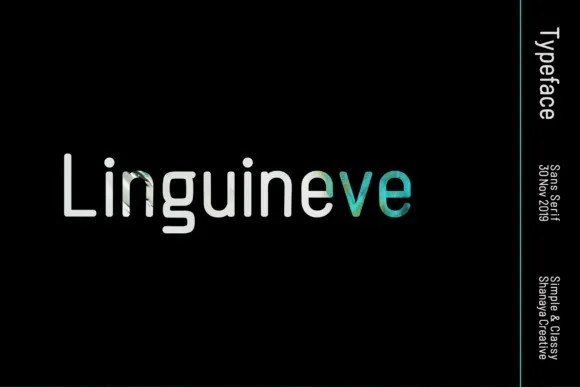
Linguineve Sans Font – Download Grátis
Esta é uma fonte sans-serif com vários estilos diferentes. Essa fonte foi projetada usando princípios geométricos, tornando-a perfeita para seus projetos criativos. Linguineve Sans Font é uma criação de Shanaya Creative. Inspirada nos palcos de teatro, a Linguineve Sans Serif se destaca pela legibilidade que permite sua utilização em um vasto leque de ocasiões de design. Seu design versátil é ideal para headlines, logotipos e marca, displays, convites, cartazes, embalagens, cabeçalhos de blogs, cartões-de-receita, cartas-postais e muito mais.